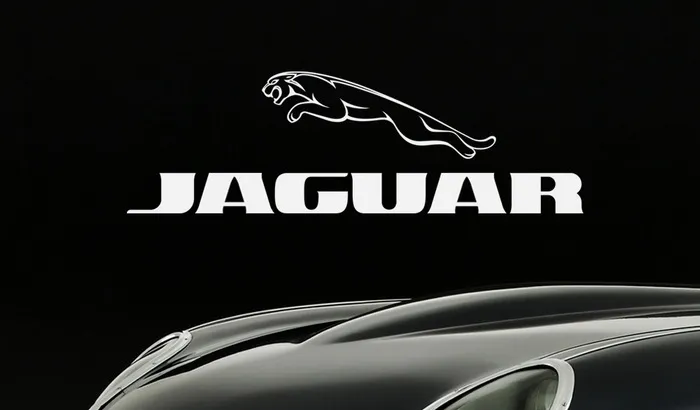
Estou aqui uma nova descrição para a página de download da fonte “Ascardi Sans Font”, que segue as regras fornecidas: Revelamos à você Ascardi Sans, uma fonte sem serif que nos transporta para o período retrô dos anos 1960 e depois. Desenvolvida pelo designer Hamilton, essa fonte retrata a arte americana do século passado através de anúncios publicitários e gráficos italianos. Ascardi Sans é uma escolha ótima para headlines e identidades corporativas. Essa fonte sem serif se tornou a companheira perfeita para ambientes que valorizam o clássico, mas não recorrem ao estereótipo dos anos 1980. Ela combina facilmente com textos mais formais e moderniza qualquer design do começo ao fim. Ascardi Sans é uma fonte sem serif perfeita para criar um design que valorize a história, enquanto também se mantém atual e progressista. Ideal para qualquer aplicação de design, desde rótulos de embalagem até materiais de marketing digital, Ascardi Sans está aqui para fornecer personalidade e estilo único a seus projetos visuais. Alguém já experimentou ou trabalhou com a Ascardi Sans? Compartilhe sua experiência em nosso blog.